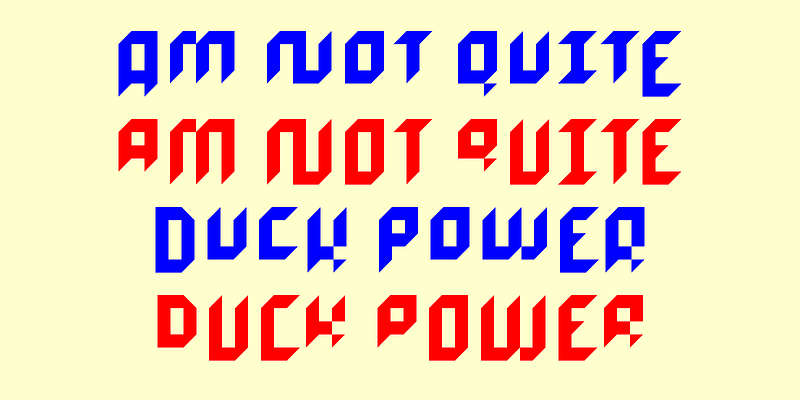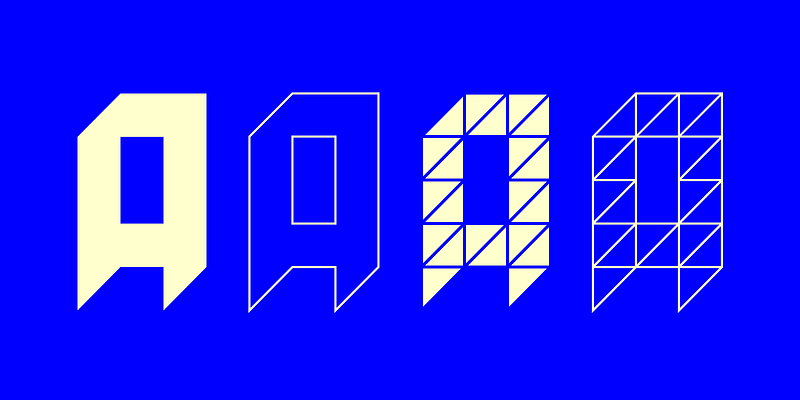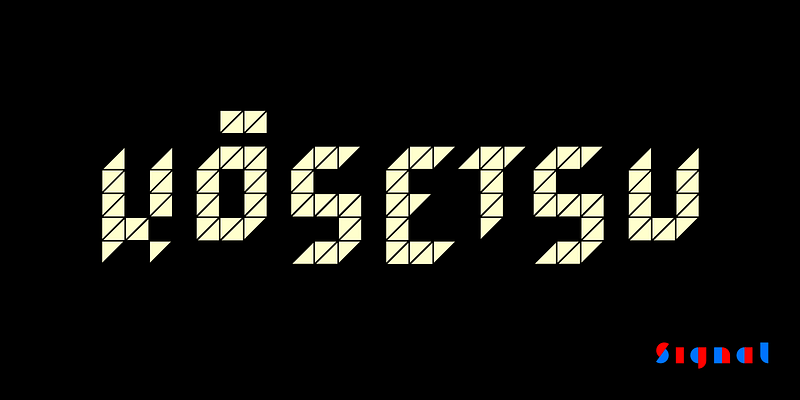
Kōsetsu (“nevada“ en japonés’) es un ejercicio de contención, un tipo de letra modular en mayúsculas basado en una retícula y ensamblado a partir de un único triángulo rectángulo isósceles. Sus formas anguladas y en bloque hacen referencia tanto a la caligrafía de plumilla ancha como a los videojuegos de 8 bits. Las letras varían en altura, creando un ritmo sincopado que los usuarios pueden controlar con un conjunto de alternativas.